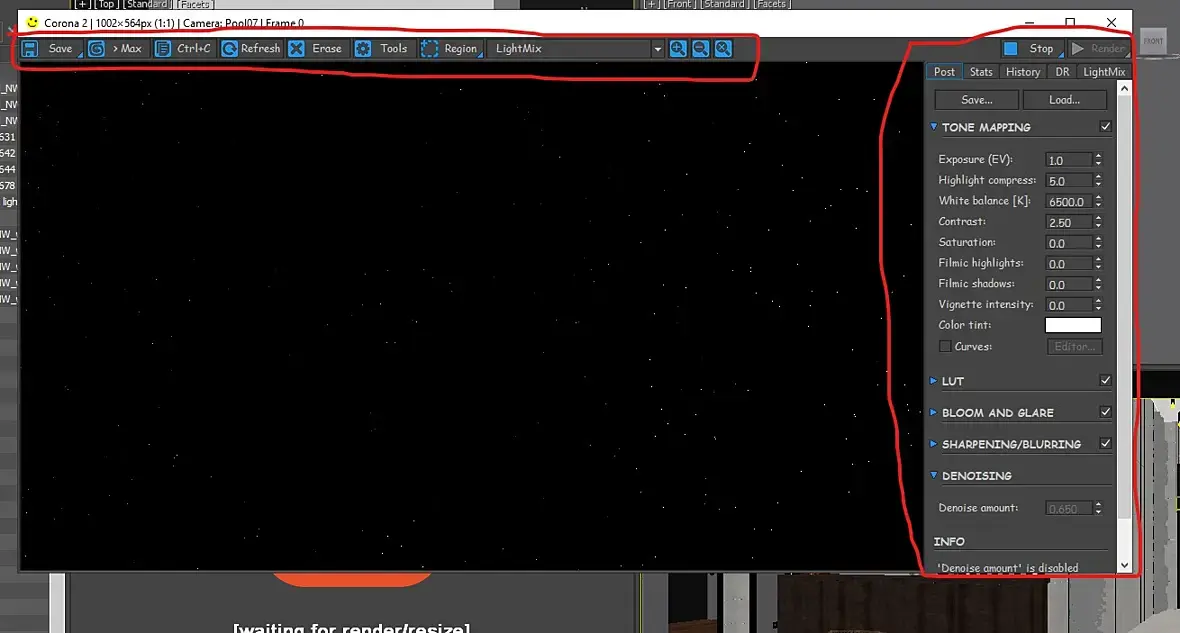
Поменялся шрифт во фрейм буфере
Включаю утром комп, загружаю 3d max, ставлю на рендер и  тут бах, замечаю что, почему то шрифт сам по себе изменился. Где это исправляется то? и как такое могло произойти?
Тоже самое произошло)) Смена шрифта..Причём даже на тех компах которые не подключены к интернет..Может вирусняк 1-во апрельский???))) Радует что хоть не на Китайский замена произошла))
Всё нормально - это у всех сегодня! Завтра "пройдет"))))))
Каждый год одно и то же, шутка уже не смешная.
Шутка, с прошлого года. Надо бы что нибудь поновее придумать. Например розовый фрейм.
а мне нравится красиво  выглядит)
Действительно заезженная шутка..В новых версиях наверное при запуске рендера, в окне фреймбуфера будет крутиться "колобок" и злорадно усмехаться до 2 апреля)))
В короне вообще можно как нибудь шрифт поменять на свой?
Млин....у меня сменился тоже, реально без шуток
а это и не шутка вовсе )
блин еще и на comic sans!))))это эпик фэйл!))))
да да, есть такое. В прошлом году тоже было))
Такое бывает каждый год - первоапрельская шутка же, алё.
А шрифт классный, жаль что он не всегда такой smiley-angel.gif
Ничосе.. smiley-unknw.gif  А я думаю, че за глюк с утра с шрифтом..
Прям божественные чудеса.
Интересно, там в соседней теме про большое количество светильников freezemaximus скрины прикладывает с таким шрифтом - он тоже пошутил???
У меня тоже на всех рабочих компах поменялся. А как вообще технически такое можно провернуть?
Да, но никто не оценил (